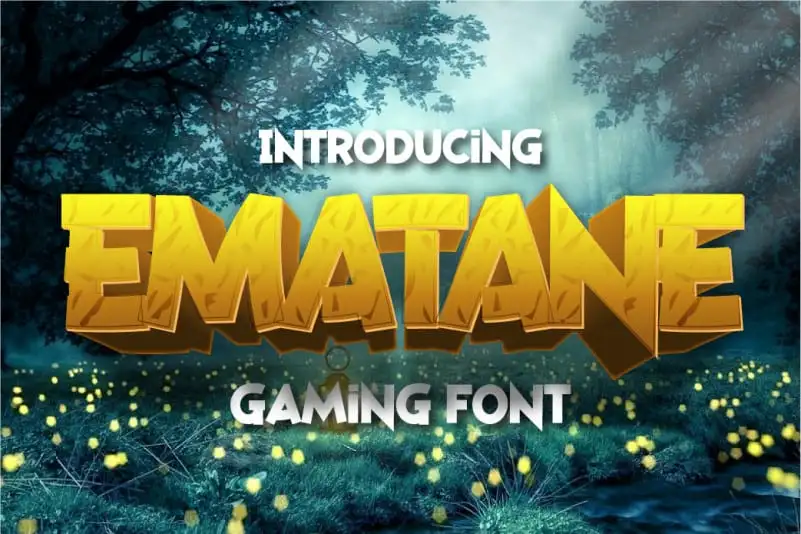
Ematane Display Font
A Ematane Display Font é uma escolha ideal para quem busca um estilo moderno e versátil para seus projetos digitais. Com seu novo visual que destaca elegância e flexibilidade, ela se destacará em qualquer projeto de design. Esta fonte possui traços robustos e claros, o que a torna irresistivelmente bela quando aplicada nos momentos certos. Seja para uma página web dinâmica ou um layout editorial sofisticado, a Ematane Display está preparada para capturar a atenção do seu público-alvo. Com sua simplicidade e força, ela se adequará perfeitamente aos seus esforços de design visual. Seja criativo com essa fonte poderosa e confiável que não deixará você insatisfeito.